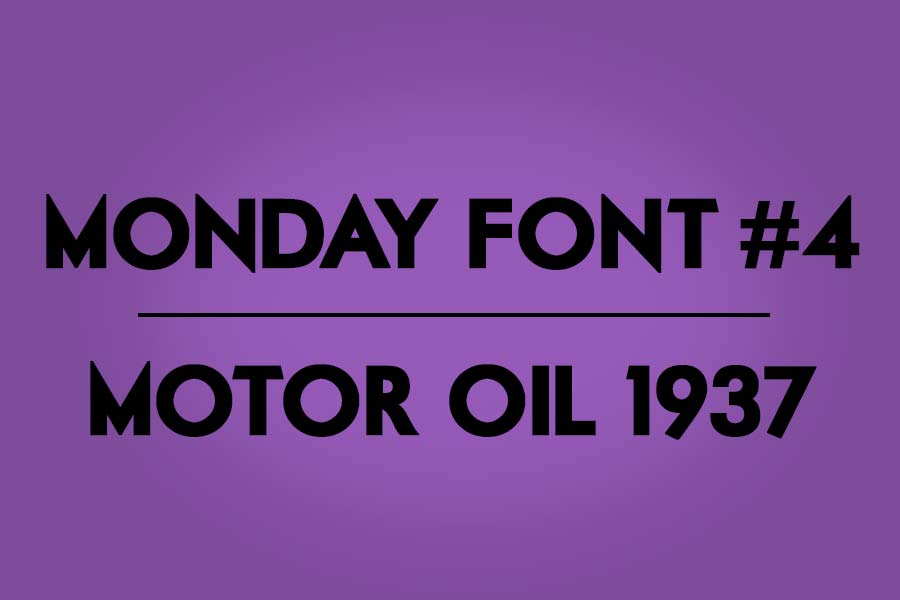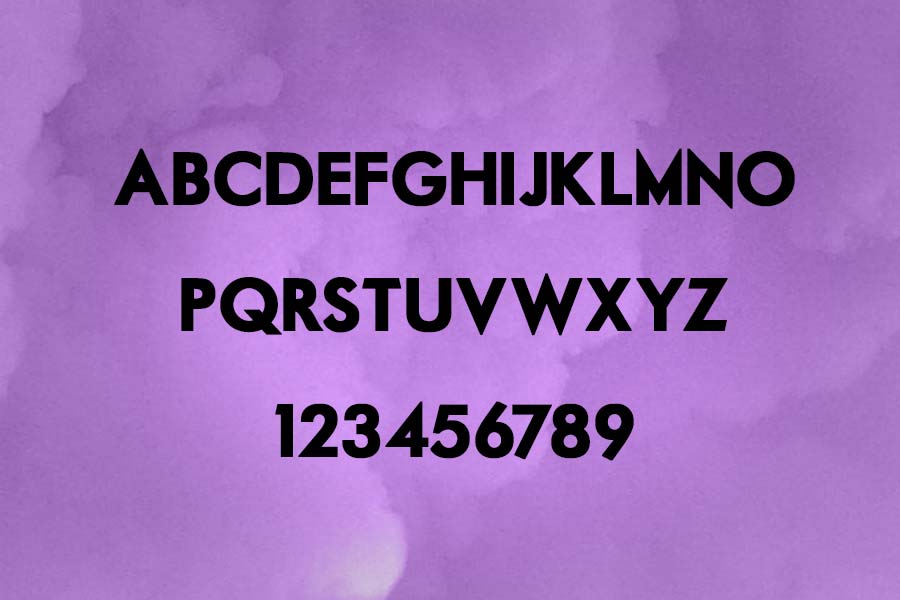
El turno de hoy es para Motor Oil 1937 , una bonita tipografía gruesa Sans Serif con sabor añejo que estamos seguros que os encantará. Creada por justme54s